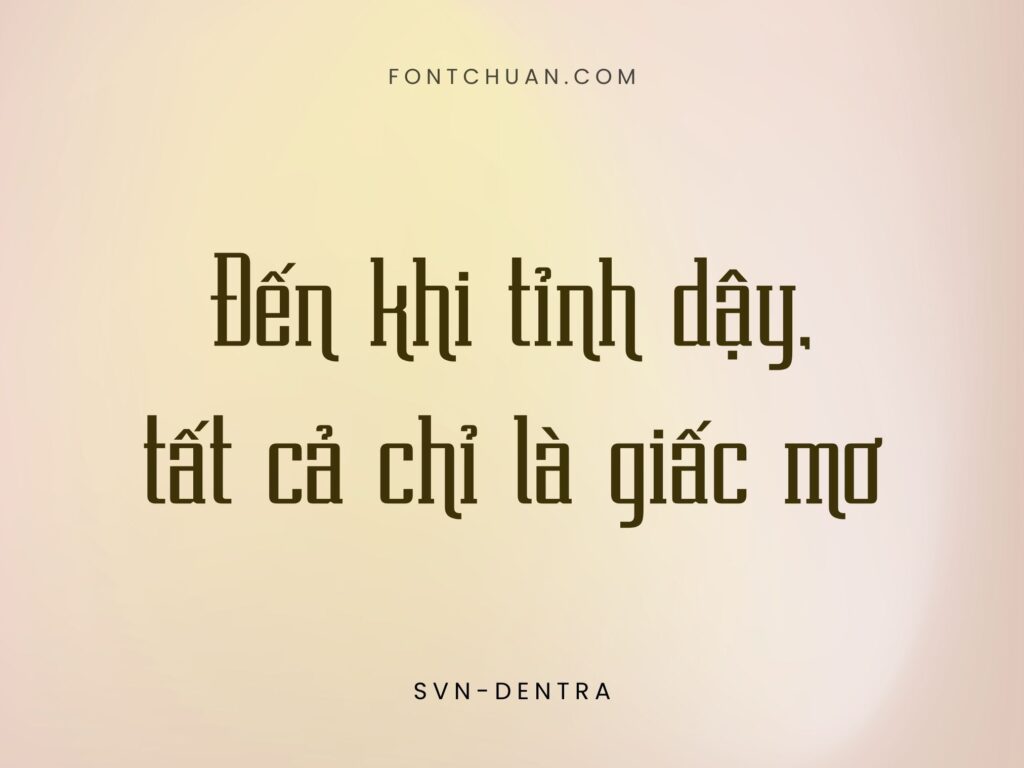
Font SVN Dentra Việt Hóa
Tác giả Font: Ferdiansyah_Ijemrockart
Font SVN-Dentra là phiên bản Việt hóa của kiểu chữ Dentra, được thực hiện bởi Styleno.1 Fonts. Dentra là một kiểu chữ mang phong cách vintage hiện đại, kết hợp giữa sự cổ điển và nét hiện đại, tạo nên sự độc đáo và thu hút trong thiết kế. Font này thích hợp cho nhiều mục đích sử dụng khác nhau, từ thiết kế logo, tiêu đề đến các ấn phẩm quảng cáo.
SVN-Dentra lý tưởng cho các dự án thiết kế yêu cầu sự kết hợp giữa cổ điển và hiện đại, như thiết kế logo, tiêu đề, bao bì sản phẩm và các ấn phẩm quảng cáo. Các ngành nghề như quảng cáo, thiệp cưới và ẩm thực có thể tận dụng font này để tạo điểm nhấn trong thiết kế. Ngoài ra, font cũng thích hợp cho các sự kiện như Tết, Giáng sinh, Valentine và các lễ hội khác.